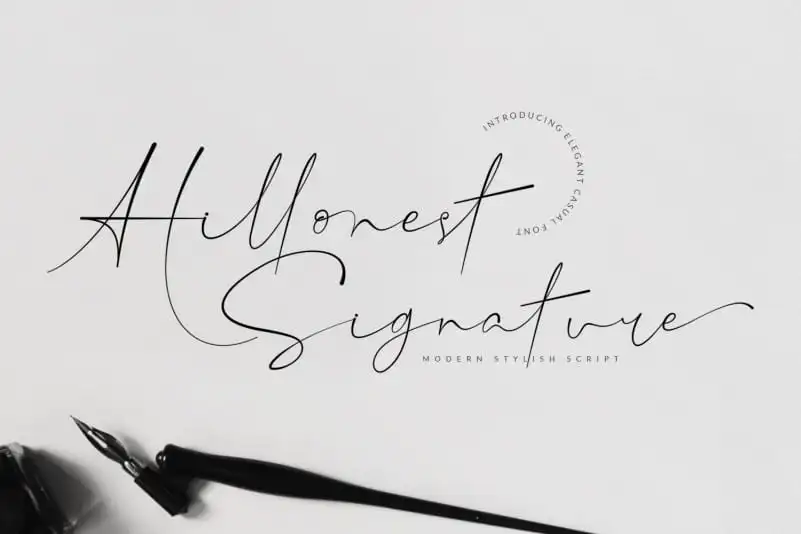
Hillonest Signature Font – Download Grátis
A fonte Hillonest Signature Font é uma escolha elegante para qualquer projeto que exija um toque delicado e pessoal do mundo da escrita a mão. Com seu charme singular, essa fonte foi meticulosamente criada por Naharstd, garantindo um acabamento luxuoso perfeito para logotipos, projetos de marca, designs de casa, embalagens de produtos, mugs personalizados, cartazes, sacolas de shopping, camisetas desenhadas à mão, capas de livros, nomes em cartão postal, convites, bonitas cartas de agradecimento e etiquetas. Seja para um simples quote ou uma produção visual complexa, Hillonest Signature Font traz elegância e personalidade à sua paleta de recursos gráficos. Suave e envolvente, essa fonte irá deixar seu design inovador e ao mesmo tempo suave na superfície da web ou impressão.
Designer: Naharstd